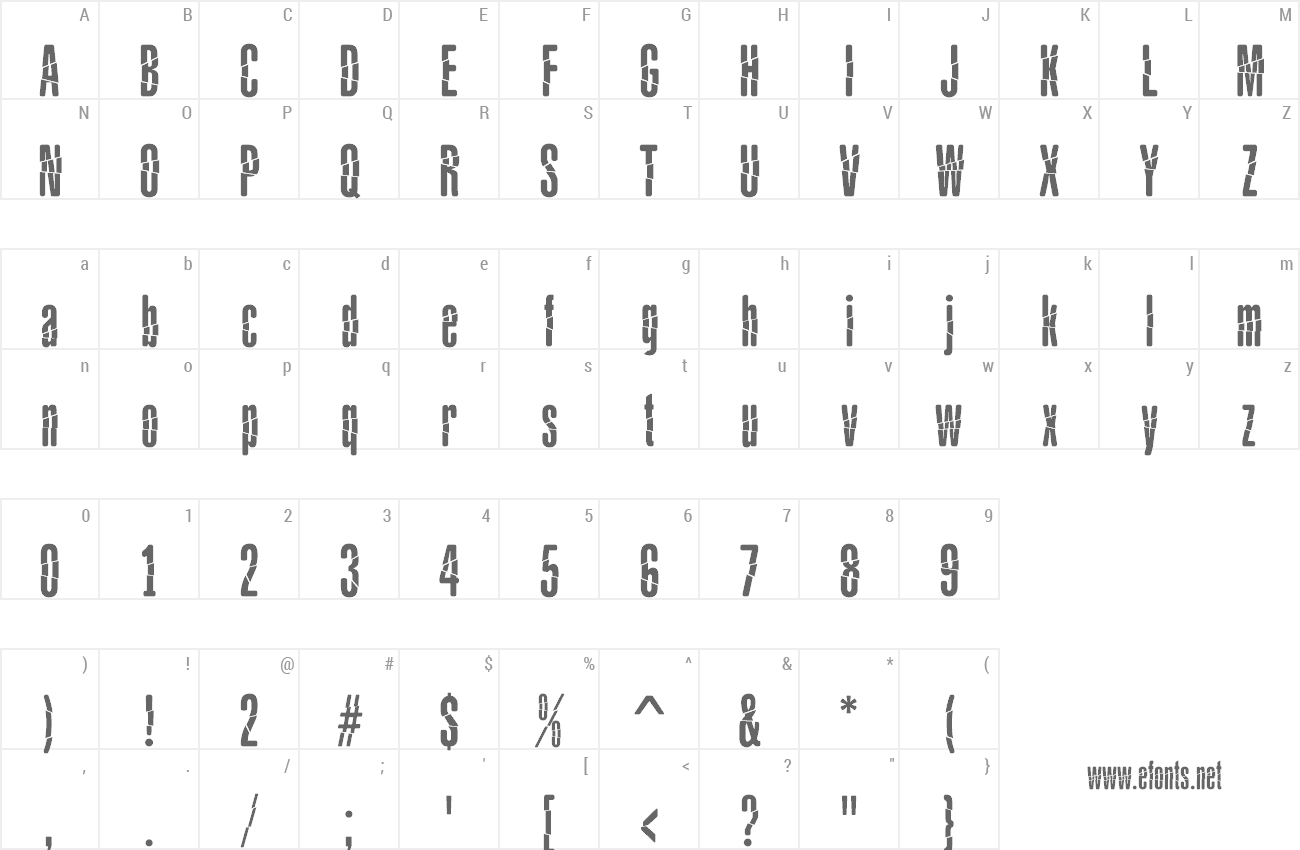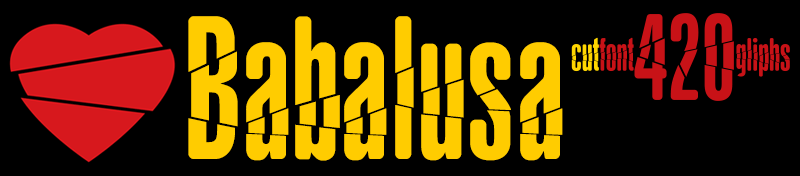
| Font name: | Babalusa Cut |
| Author: | deFharo |
| Note by deFharo | |
Esta tipografía es un experimento de rajado y mutilación sobre mi anterior tipografía grotesca Yacarena Ultra Sans. Este ejercicio de corte aporta a la fuente una temporalidad estilística (moda) de la que no se sabe hasta cuando perdurará en el diseño gráfico, mientras tanto aprovéchala en composiciones de diseño de carteles, publicidad o para titulares en diseño editorial. =========== This typeface is an experiment in cracked and grotesque mutilation of my previous Yacarena Ultra Sans typeface. This exercise gives cutting power temporality stylistic (mode) of which is not known until they endure in graphic design, meanwhile kicking butt in compositions poster design, advertising or editorial design headlines. =========== • Sólo para uso personal. • Licencia comercial disponible • Only for personal use. • Commercial license. https://defharo.com/fonts/babalusa-cut-font/ |